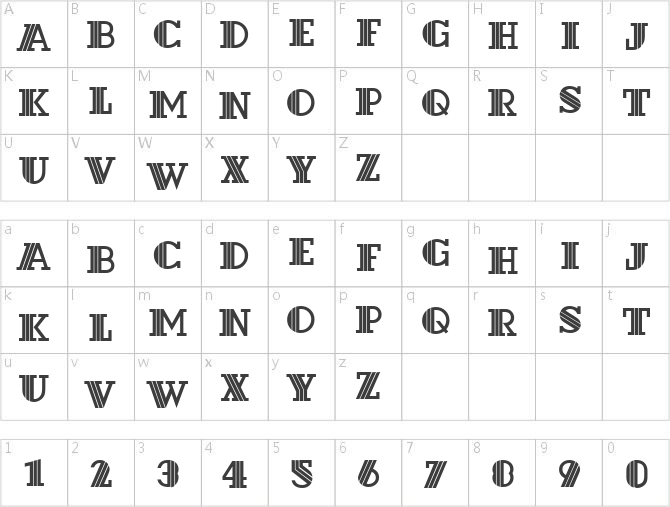
字體名稱: MAK Dex
MAK DextorSP68
MAK DextorSP68介紹
MAK DextorSP68字體MAK Dextor字庫是一款讓人賞心悅目、百看不厭的英文字體,適合各類廣告和產品包裝設計應用,字體大小0.06MB,格式為ttf字體,上傳用戶是Elieen,作者/版權方為未知